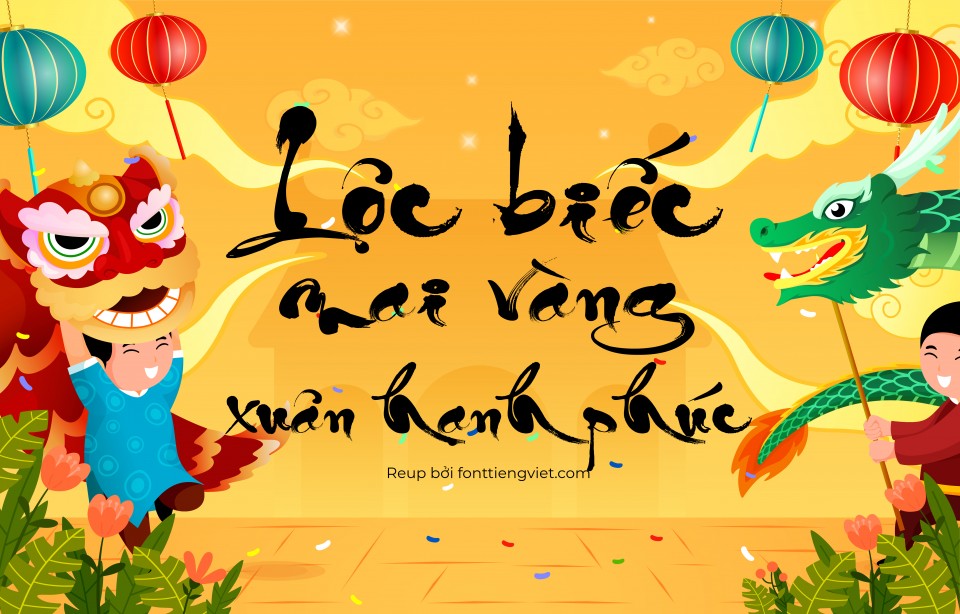
Tải Font thư pháp Công Thuỷ – Tết Miễn Phí Đẹp Nhất Cho Năm Mới
Chào đón không khí rộn ràng của những ngày cuối năm, việc tìm kiếm một bộ Font Chữ mang đậm bản sắc văn hóa Việt để thiết kế thiệp chúc mừng, câu đối hay banner sự kiện là nhu cầu thiết yếu. Trong đó, bộ Font thư pháp Công Thuỷ – Tết nổi lên như một lựa chọn hàng đầu nhờ sự kết hợp tinh tế giữa nét bút mực tàu truyền thống và công nghệ kỹ thuật số hiện đại. Đây là bộ font được cộng đồng thiết kế đánh giá cao bởi sự mềm mại, uyển chuyển nhưng vẫn giữ được sự rõ ràng, dễ đọc trên nhiều thiết bị khác nhau.
Đặc điểm nổi bật của Font thư pháp Công Thuỷ – Tết trong thiết kế
Nét vẽ thủ công đầy tính nghệ thuật
Bộ Font thư pháp Công Thuỷ – Tết tái hiện chân thực những đường nét nhấn nhá của nghệ thuật thư pháp Việt Nam. Từng ký tự được chăm chút tỉ mỉ, tạo cảm giác như được viết trực tiếp từ tay các thầy đồ. Điều này giúp các sản phẩm thiết kế như bao lì xì, thực đơn nhà hàng hay bảng hiệu trường học trở nên trang trọng và ấm cúng hơn trong dịp Tết nguyên đán.
Khả năng tương thích và Việt hóa hoàn chỉnh
Cách ứng dụng Font thư pháp Công Thuỷ – Tết hiệu quả
Để tạo nên một tác phẩm đẹp, bạn nên kết hợp font này với các tông màu đỏ, vàng hoặc nền giấy xuyến chỉ. Việc sử dụng Font thư pháp Công Thuỷ – Tết làm tiêu đề chính sẽ tạo điểm nhấn thị giác mạnh mẽ, thu hút người xem ngay từ cái nhìn đầu tiên. Đừng quên tải ngay bộ Font Miễn Phí, Font Việt Hóa, Font thư pháp Công Thuỷ – Tết để làm phong phú thêm kho tàng tài liệu sáng tạo của mình nhé.